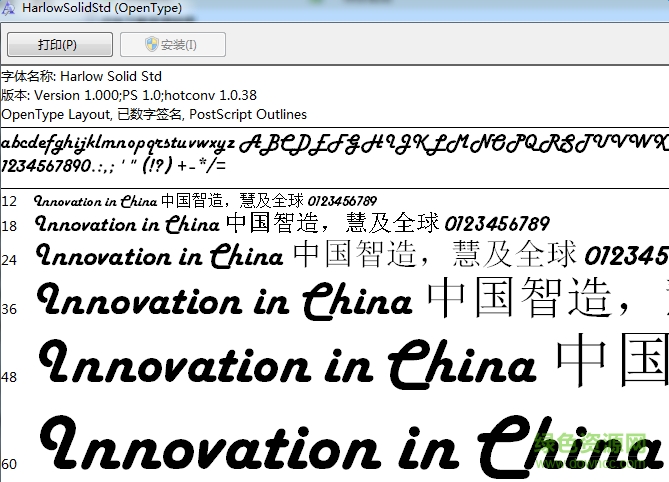
HarlowSolid英文字體
HarlowSolid字體是一款超好用的個(gè)性英文字體,該字體可以廣泛應(yīng)用于廣告設(shè)計(jì)、宣傳海報(bào)、ppt、影視制作以及任何使用文字的領(lǐng)域,有需要的朋友可以免費(fèi)下載收藏。
HarlowSolid字體
HarlowSolid字體是一款極具個(gè)性的字體,該字體十分飄逸,彰顯了自己的個(gè)性,有喜歡的朋友可以來(lái)綠色資源網(wǎng)下載使用!